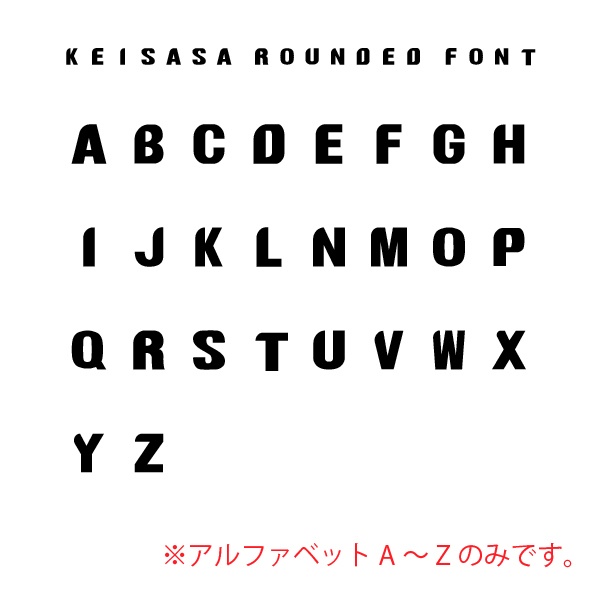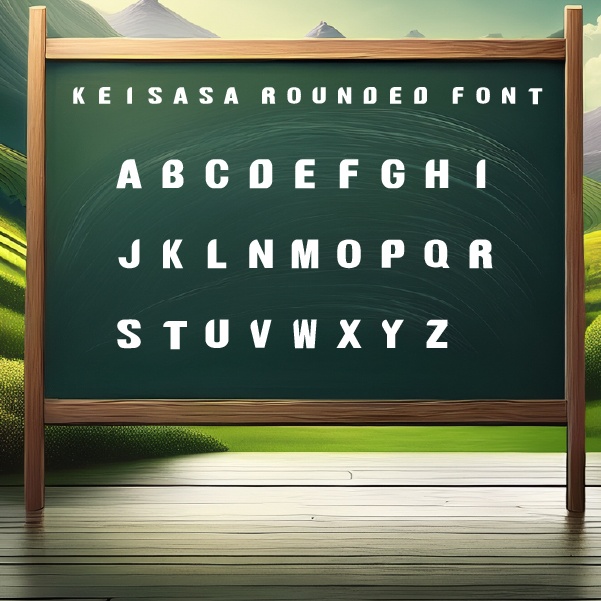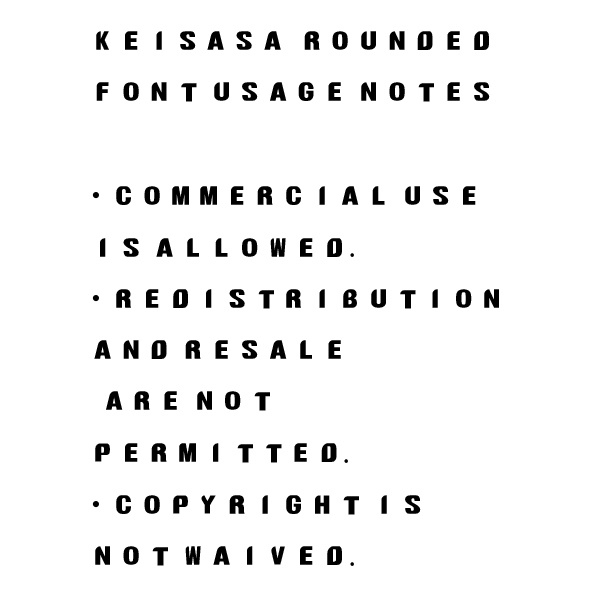
【商用可】Keisasa Rounded Font︱ 片角だけまるい、遊び心あるサンセリフ
Keisasa Rounded Fontは、片側の角だけを丸めた特徴的なデザインが魅力のサンセリフ体です。 モダンで個性的な印象を持ちながらも、読みやすさを保つため、ロゴ・パッケージ・見出し・ポスターなど幅広いデザインに適しています。 ポップな色合いや遊び心のあるグラフィックと組み合わせることで、独自の世界観を表現できます。 商用利用可能です。 ※アルファベットA~Zのみの収録となります。ご注意ください。 Keisasa Rounded Font is a unique sans-serif typeface with one-corner rounded details. It combines modern minimalism with a playful touch, making it perfect for logos, packaging, posters, and headlines. Pair it with vibrant, colorful backgrounds to create a bold and cheerful design impression. Commercial use allowed. Only uppercase A–Z characters are included. Please note.